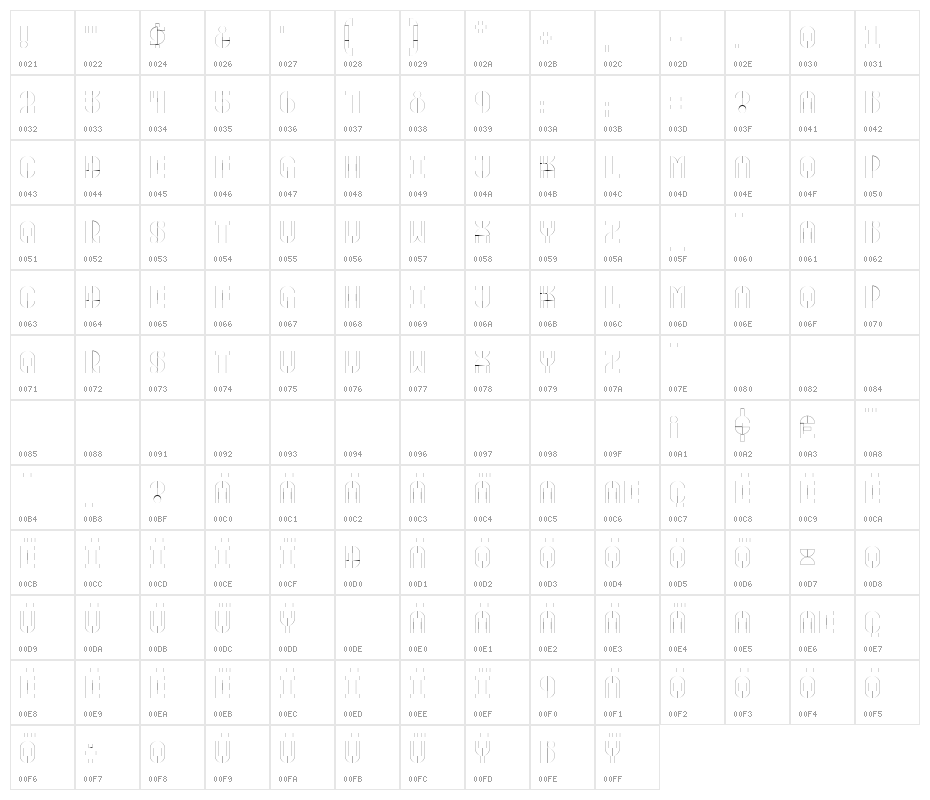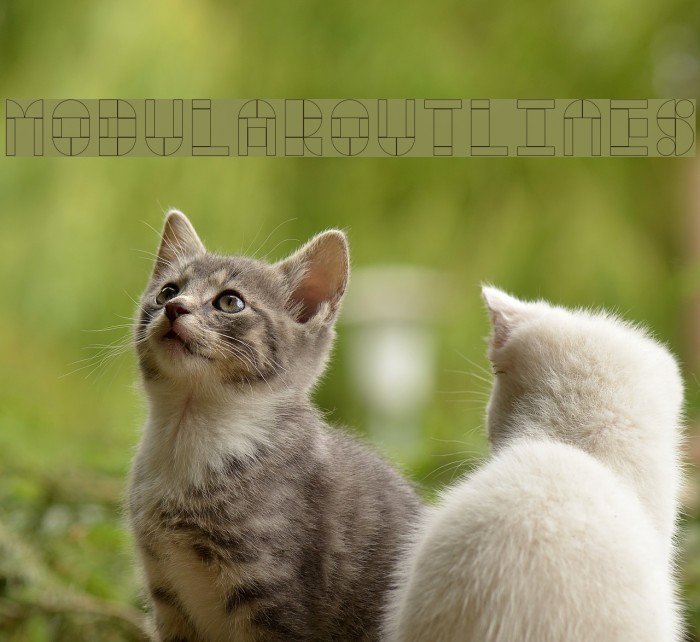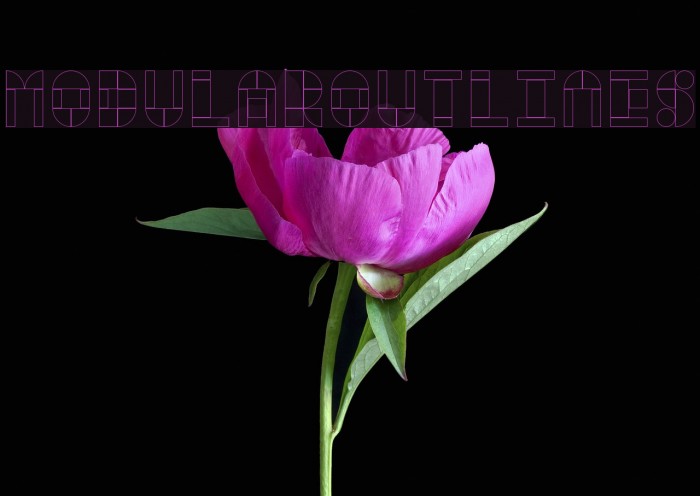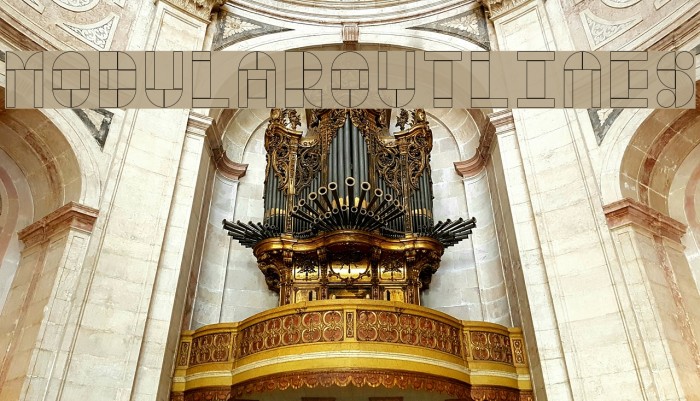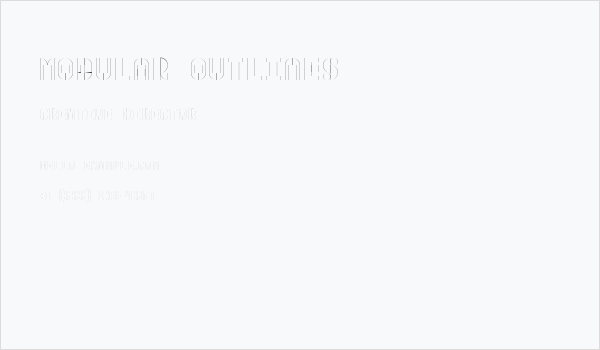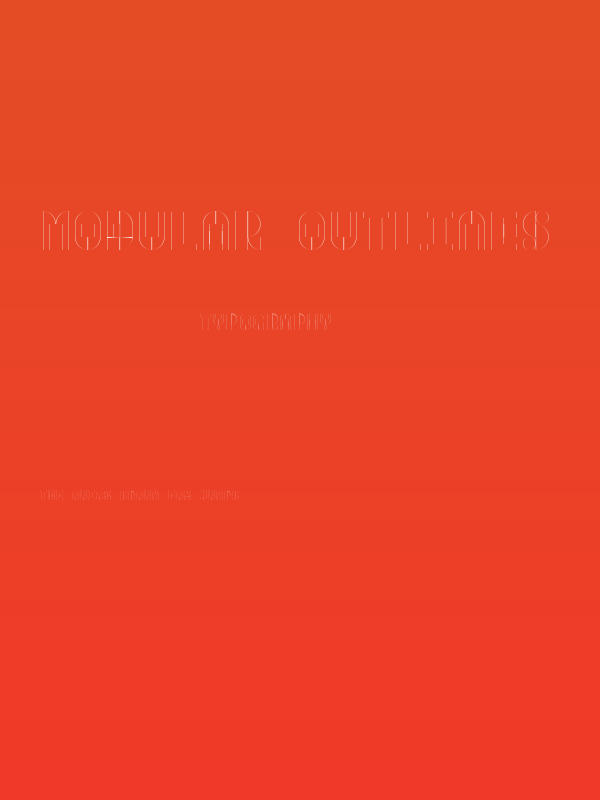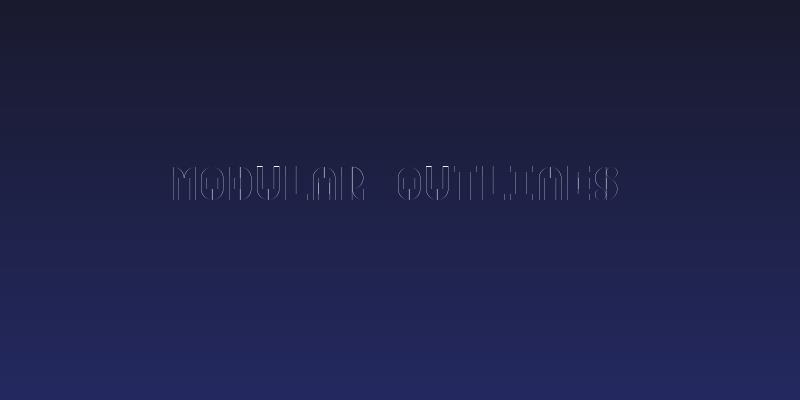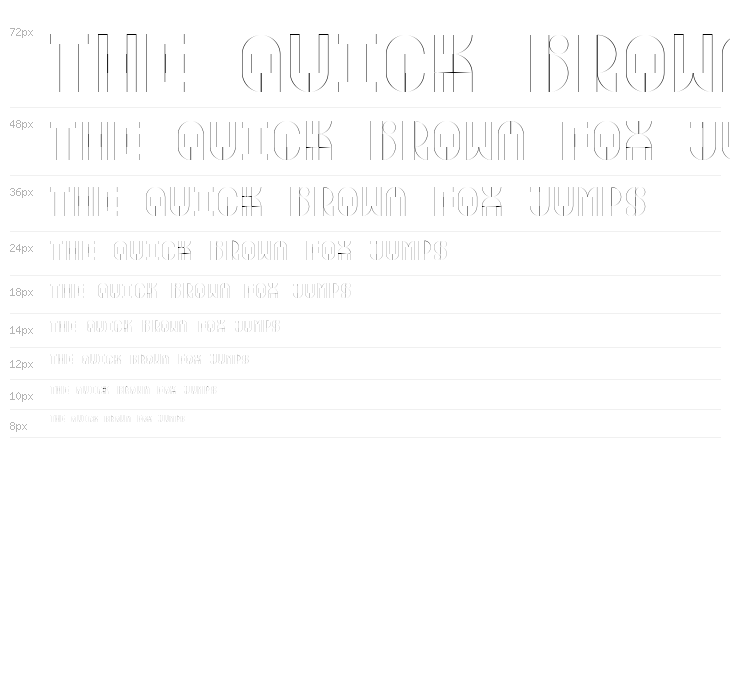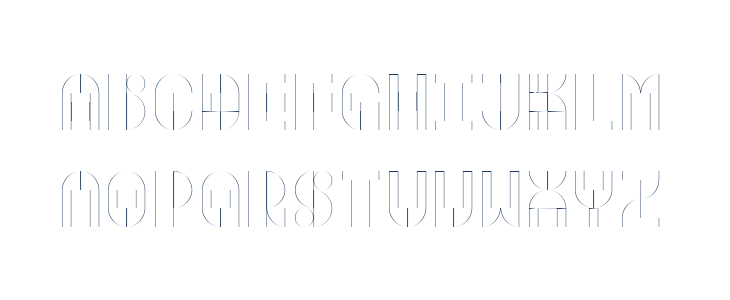
Modular Outlines Font
| Proyectos propuestos | Ideal for modern branding, tech-related projects, futuristic posters, and digital art where a unique and eye-catching typeface is desired. |